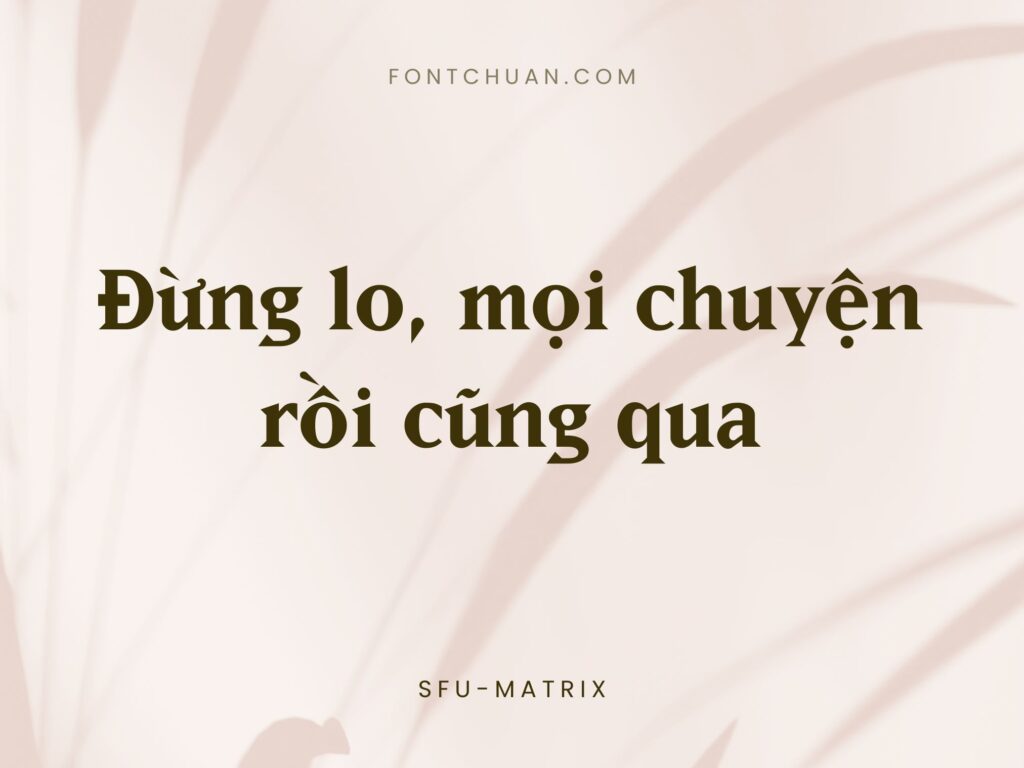
Matrix là một kiểu chữ serif được thiết kế bởi Zuzana Licko và phát hành lần đầu tiên vào năm 1986 thông qua Emigre Fonts. Font này được sưu tầm và đăng bởi thành viên của Font Chuẩn. Với thiết kế độc đáo và hiện đại, Matrix đã trở thành một lựa chọn phổ biến trong nhiều dự án thiết kế đồ họa và in ấn. Ngoài ra, Matrix cũng có thể được sử dụng như một Font sinh nhật, lý tưởng cho các thiệp mừng, poster hay banner sự kiện, giúp tạo ra không khí vui tươi, ấm áp và thu hút người xem.
Đặc biệt, Matrix rất phù hợp khi sử dụng làm Font logo cho thương hiệu hoặc trở thành Font chữ quảng cáo trong các chiến dịch truyền thông, nhờ khả năng tạo ấn tượng thị giác mạnh mẽ. Ngoài ra, Matrix cũng có thể được ứng dụng như một Font sinh nhật, lý tưởng cho các thiệp mừng, poster hay banner sự kiện, giúp mang đến không khí vui tươi, ấm áp và thu hút người xem.
Về mặt thiết kế, Matrix kết hợp các yếu tố của kiểu chữ serif truyền thống với sự sáng tạo hiện đại, tạo nên sự cân đối giữa tính dễ đọc và thẩm mỹ. Font này hỗ trợ nhiều ngôn ngữ và bao gồm các ký tự đặc biệt, giúp người dùng dễ dàng tùy chỉnh theo nhu cầu. Matrix thường được sử dụng trong các thiết kế sách, tạp chí, nhận diện thương hiệu và các dự án cần sự trang trọng và chuyên nghiệp. Các ngành nghề như xuất bản, quảng cáo, và thiết kế đồ họa có thể tận dụng kiểu chữ này để tạo dấu ấn đặc biệt trong truyền thông.